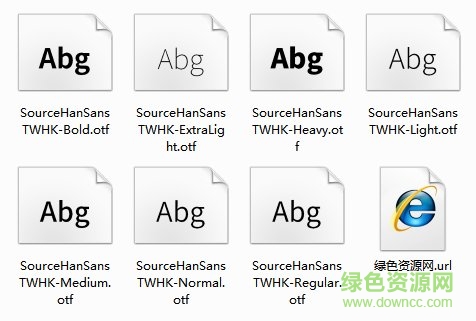
思源黑體臺(tái)灣版ttf一共包含了七款不同的字體文件。思源黑體在多個(gè)行業(yè)領(lǐng)域都很受贊!字體外觀規(guī)整整潔,可以用來(lái)設(shè)計(jì)報(bào)紙、海報(bào)等等。需要的朋友快來(lái)綠色資源網(wǎng)下載吧。
思源黑體是Adobe與Google歷時(shí)三年在2014年7月宣布推出的一款開源字體,這是一款新的供桌面使用的開源 Pan-CJK 字體家族, 有七種字體粗細(xì)(ExtraLight、Light、Normal、Regular、Medium、Bold 和 Heavy),完全支持繁體中文、簡(jiǎn)體中文、日文和韓文,這些全部都包含在一種字體中。它還包括來(lái)自我們頗受歡迎的 Source Sans字體家族的拉丁文、希臘文和西里爾文字形。
該款字體是由Google和Adobe合作開發(fā)的。Google將其命名為Noto SansCJK,作為Google的Noto字體家族的成員。Adobe則命名為Source Han Sans,作為Adobe的Source字體家族的一員。Adobe擁有字體設(shè)計(jì)的版權(quán)。發(fā)布的字體文件則可以不受限制的免費(fèi)使用。這些字體文件使用Apache許可證版本2(ApacheLicense, Version 2)